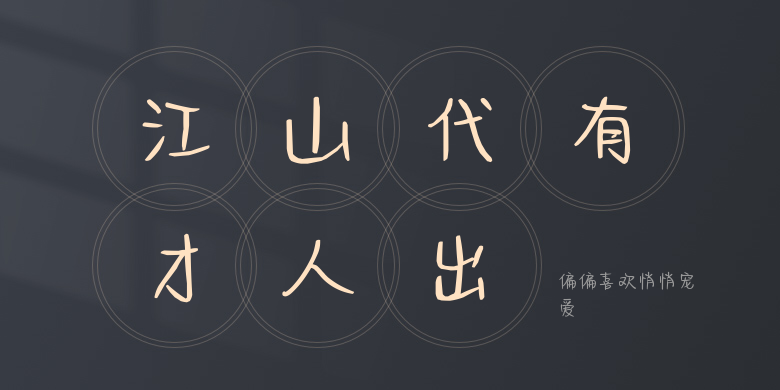
偏偏喜欢悄悄宠爱
偏偏喜欢悄悄宠爱,这款字体结构工整、笔画清晰,兼顾美观与易读性,适用于标题、正文、海报、包装、LOGO 等多种场景。字形优雅稳定,风格百搭耐看,适配日常排版与创意设计,让文字呈现更舒适、更具质感。偏偏喜欢悄悄宠爱一笔一画,皆是细节,以均衡的比例、流畅的线条打造舒适视觉体验,字形端正大气,风格简约现代。无论是商业设计、品牌宣传还是日常排版,都能轻松驾驭,让文字更有格调与力量。偏偏喜欢悄悄宠爱字体下载。